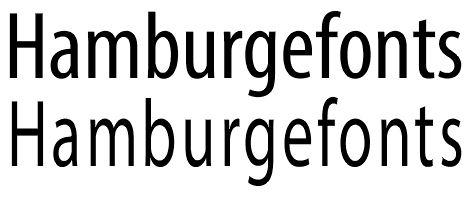
Condensed-Schriften und gestauchte Schriften
Kann jemand die Definition der beiden Schriftschnitte "Condensed-Schriften" und "gestauchte Schriften" nennen und was bei deren Nutzung beachtet werden muss, beziehungsweise was nicht falsch gemacht werden darf?
• Condensed-Schriften sind in der Regel "von Haus aus" gestauchte Schnitte, das heißt, die Zeichendicke bleibt gleich und ist demnach nicht verzerrt.
• Unter gestauchten Schriften versteht man im Satzprogramm gestauchte Schnitte, das heißt, man verändert nachträglich die Zeichenbreite, was zur Verzerrung der Zeichen führt.
[...] was bei deren Nutzung beachtet werden muss, beziehungsweise was nicht falsch gemacht werden darf?
Letzteres sollte man auf gar keinen Fall machen, da man durch die nachträgliche Stauchung die durchaus jahrelange Arbeit des Schriftgestalters an der Schrift und damit auch die Harmonie der einzelnen Schnitte zueinander hinübermacht.
Die Condensed-Schriften kannst du problemlos nutzen (ohne ein schlechtes Gewissen :-D).
Ich habe das mal schnell nachgestellt:
der obere Schriftzug ist die originale Condensed-Schrift, gut zu sehen, dass hier waagerechte und senkrechte Linien in der Schrift zueinander passen. der untere Schriftzug hingegen wurde aus der normalen Schrift gestaucht, was zu viel ztu dünnen senkrechten in der Schrift führt.